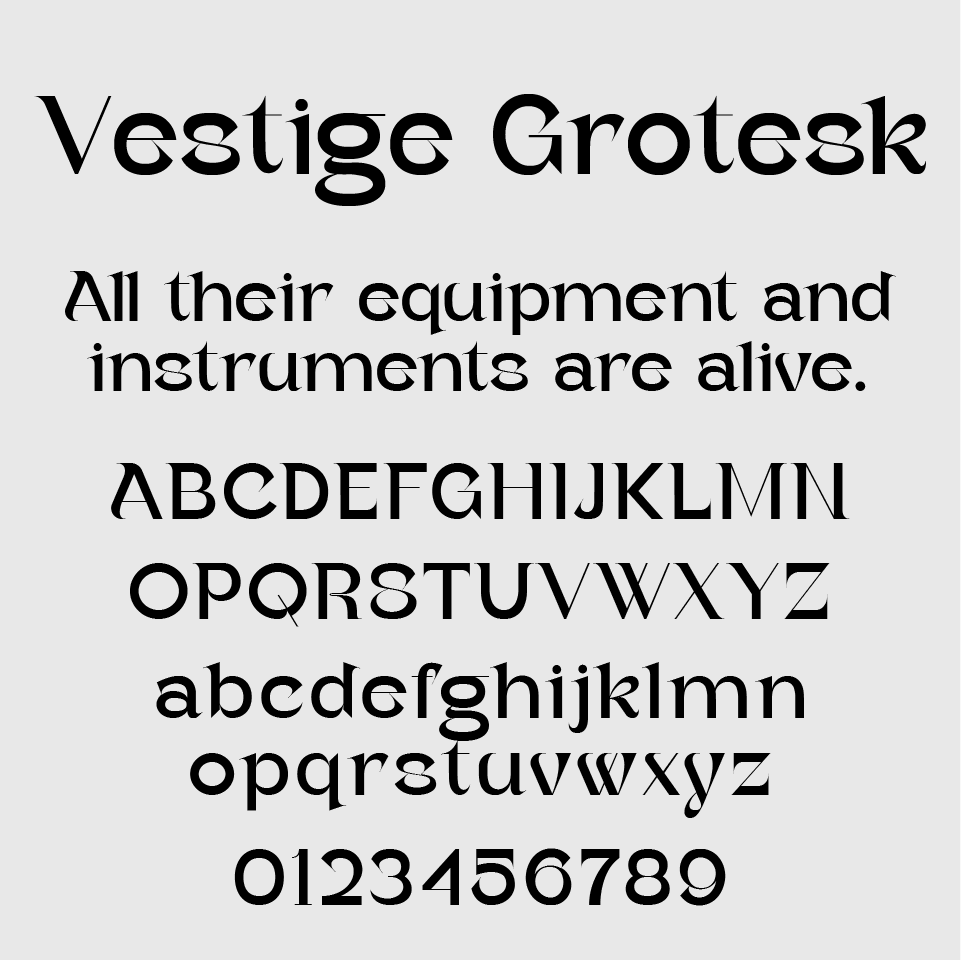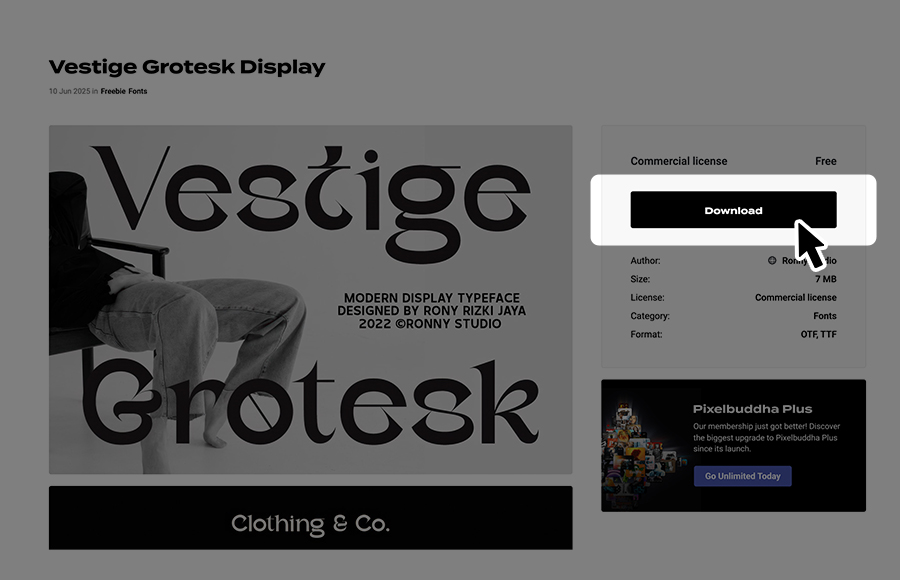
Vestige Groteskフォントは、レトロな風合いと未来的な要素が混ざり合ったユニークなデザインが特徴のディスプレイフォントです。
文字の一部に施された鋭角的なスリットや曲線的な装飾は、どこかアール・デコやSF的な世界観を思わせるデザインがとってもかっこ良いフォントです。
クラシカルなフォントに見えて、よく見ると鋭角な装飾が付いていたり、現代的で大胆なアプローチが光るこのフォントは、奇抜さを表現したいアートブックやブランドロゴ、パッケージデザインなど、印象に残る場面で効果を発揮します。